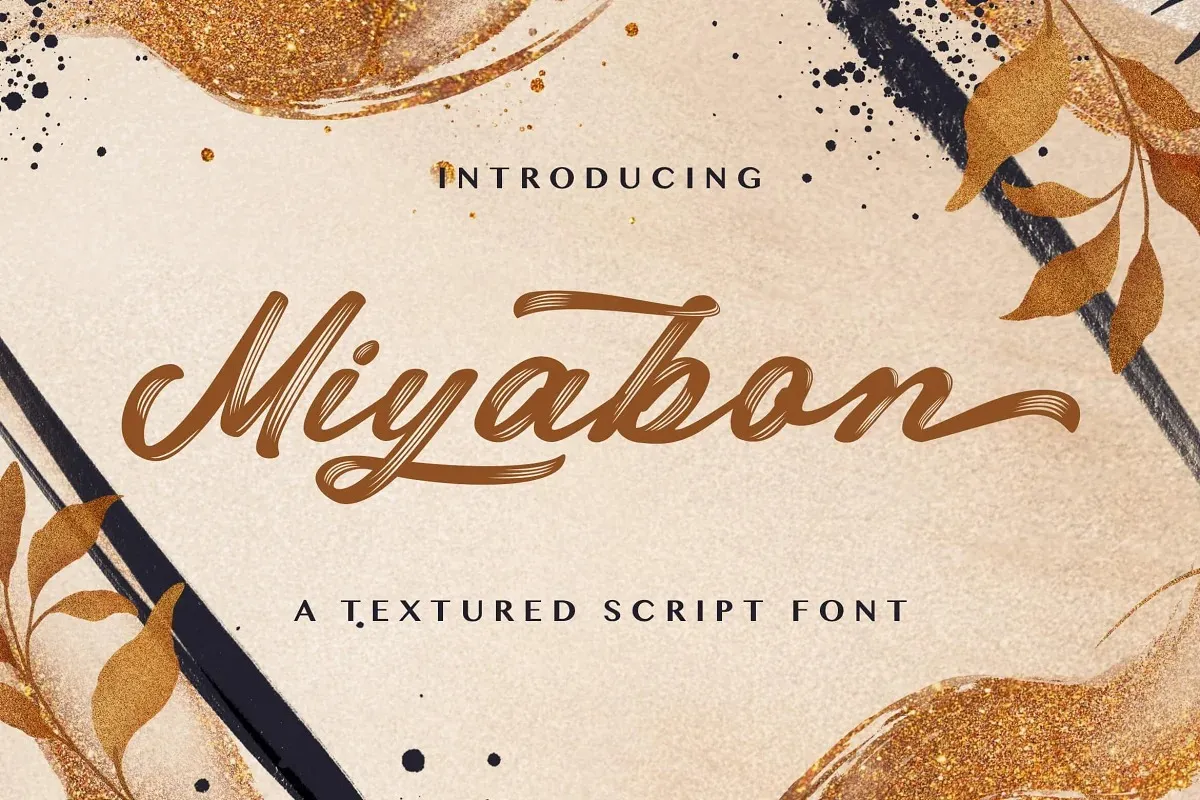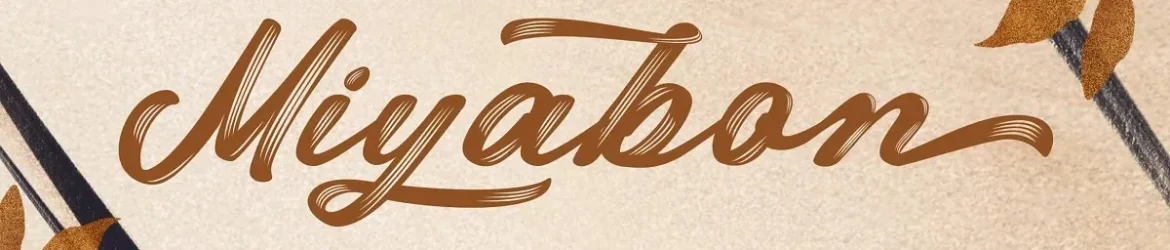
A Miyabon Font é uma fonte criada pela StringLabs com estilo de pincel, perfeitamente projetada para uma variedade de usos. Seu formato artesanal e fluido fazem dela uma escolha incrível para projetos de marca, logomarcas, capas de livros, desenhos para camisetas, posts em mídias sociais, anúncios, embalagens de produtos, designs de produtos, selos, marcas d’água, convites e materiais de correspondência. Além disso, sua facilidade na criação de letras distintas torna-a ideal para qualquer projeto que exija uma personalização atraente. Com a Miyabon Font, você pode dar um toque especial ao seu trabalho gráfico sem grandes dificuldades.